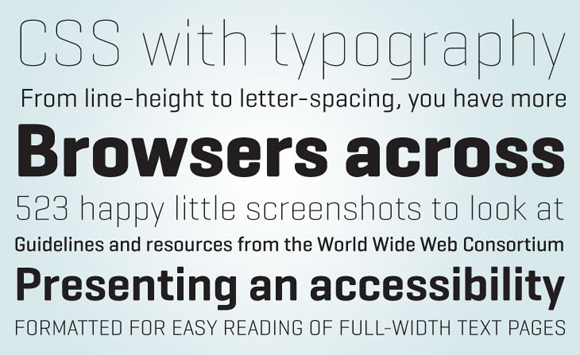
Eduardo Manso nos presenta la última creación de su fundición Emtype. Se trata de un diseño de «palo seco» que presenta una estructura semimodular y unos acabados ligeramente redondeados que la hacen transmitir un tono cálido y que con un buen rango de «pesos» nos asegura que la podremos utilizar en composiciones complejas donde tengamos que marcar las diferencias.